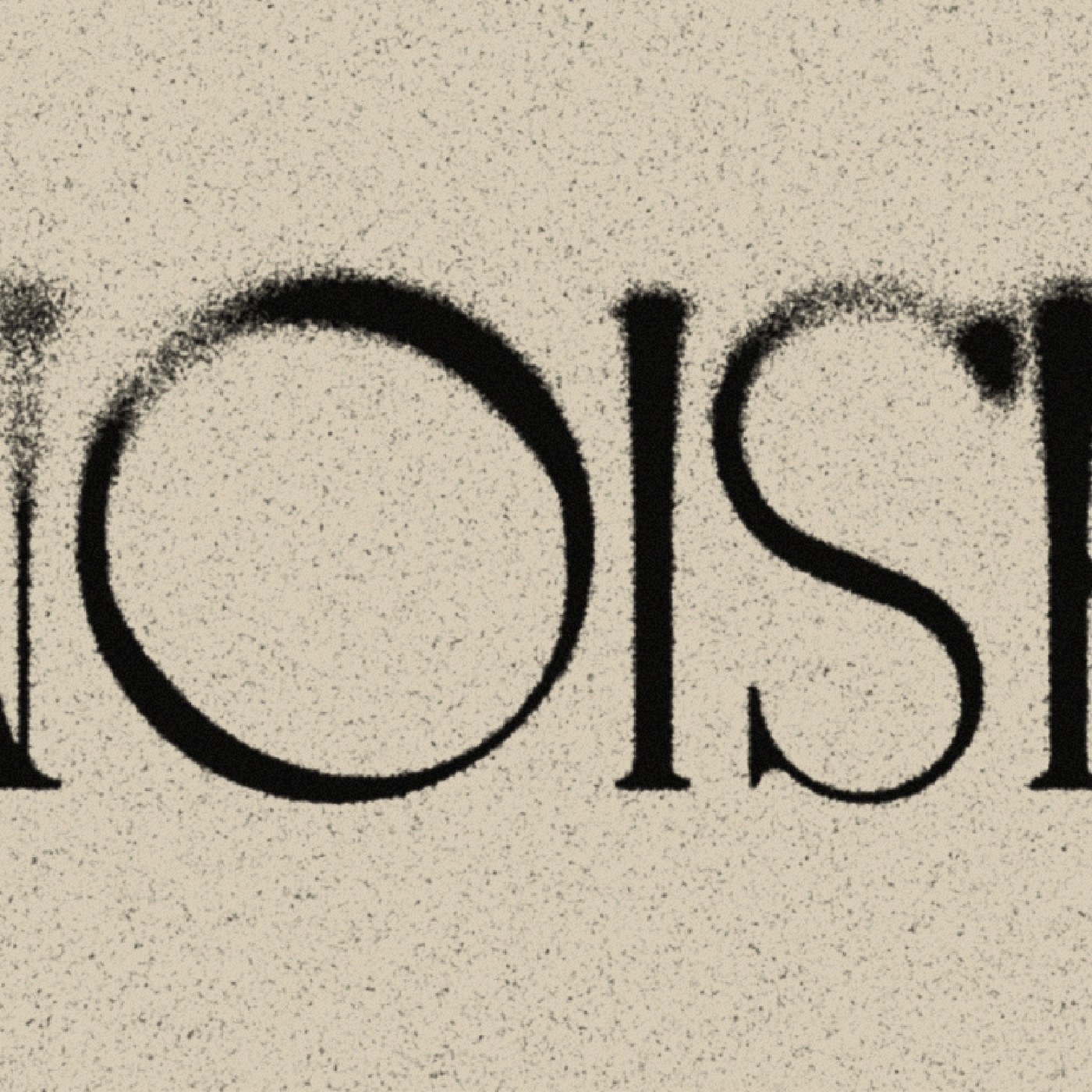
Diseño de movimiento de tipografía dinámica: el texto se mueve como un cuerpo
La segunda colección de Knife Motion muestra cómo el diseño de movimiento tipográfico dinámico puede trascender los ajustes preestablecidos de software estilizados y sentirse como una cualidad física.
Cuatro secuencias de la serie tratan a los personajes como objetos físicos. Las letras se aceleran, chocan, resisten y se liberan dentro de una estricta cuadrícula espacial. Este enfoque define un nuevo estándar para el diseño de movimiento de tipografía dinámica utilizando fotogramas clave manuales. El movimiento exhibe inercia mecánica en lugar de una trayectoria lineal. Cada cuadro exhibe una alineación de línea de base estricta y márgenes espaciales calculados. El ritmo visual resultante se siente reflexivo y estructurado. Por tanto, el tipo se comporta como un cuerpo real reaccionando a fuerzas externas. Cada movimiento parece valioso y matemáticamente preciso.
Aplicar fuerzas físicas al diseño de movimiento de tipografía cinética.
El sistema visual se basa en una paleta de colores sobria para enfatizar la forma estructural. La fuente negra de alto contraste contrasta maravillosamente con el cálido fondo color crema arena. Esta elección de color enfatiza las limitaciones geométricas de cada tipo de letra. La paleta de colores limitada centra la atención por completo en los detalles dinámicos del diseño del movimiento de la tipografía. Las obras muestran contraste táctil a través de texturas impresas analógicas en pantallas digitales. La escala tipográfica crea tensión compositiva a medida que el texto se amplía para llenar el marco. Cada elemento está en absoluto equilibrio, manteniendo su jerarquía estructural incluso durante secuencias de rápido movimiento. Esta claridad estructural hace que la obra sea legible a cualquier velocidad.
Knife Motion logra cerrar la brecha entre una estética ambiciosa y un diseño funcional. Esta colección se encuentra en algún lugar entre una secuencia de títulos y un formato de redes sociales. Para 2026, los diseñadores de movimiento deben equilibrar estos formatos para campañas digitales y de transmisión. El equipo del estudio en el Reino Unido utilizó las piezas para demostrar cómo el peso afecta el tipo. El proyecto recibió más de 14.000 me gusta, lo que demuestra el creciente interés en el diseño de movimiento físico. Los diseñadores pueden estudiar estos bucles para comprender cómo infundir emociones humanas en las herramientas digitales. Este enfoque garantiza que el trabajo digital conserve un sentido de artesanía.